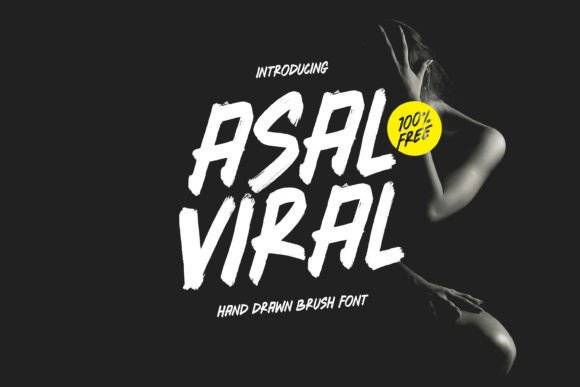
Fonte Asal Viral para títulos, pôsteres e projetos de identidade visual.
A fonte “Asal Viral” é uma fonte pincelada cativante que exala dinamismo e expressividade. Seu design apresenta traços caligráficos e texturas que lembram pinceladas, conferindo-lhe uma aparência distinta e artística. As letras são ousadas e enérgicas, com uma linha de base ligeiramente irregular, criando uma sensação de autenticidade artesanal.
A fonte possui um caráter inerentemente viral, tornando-a perfeita para designs que visam capturar a atenção e se espalhar rapidamente. O estilo único da fonte “Asal Viral” permite que ela se destaque e cause uma impressão memorável, principalmente em projetos que exigem um toque de criatividade e modernidade.